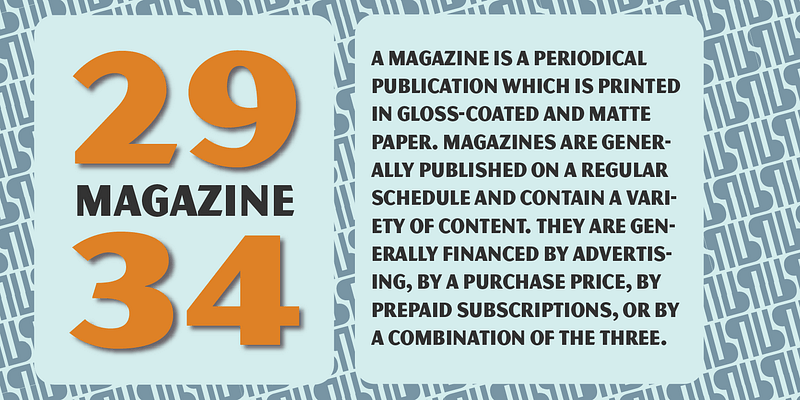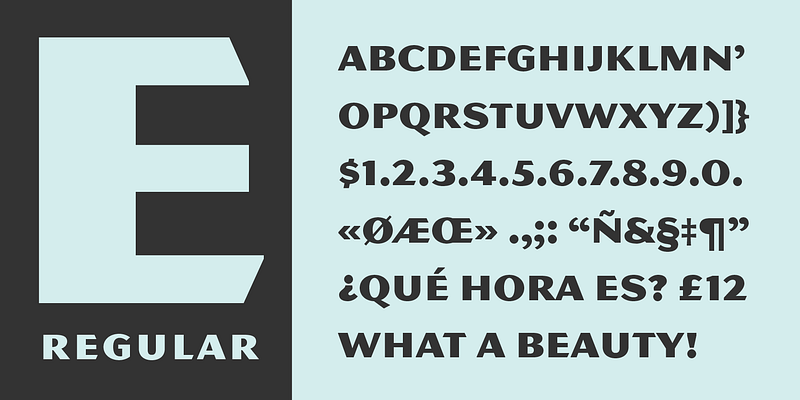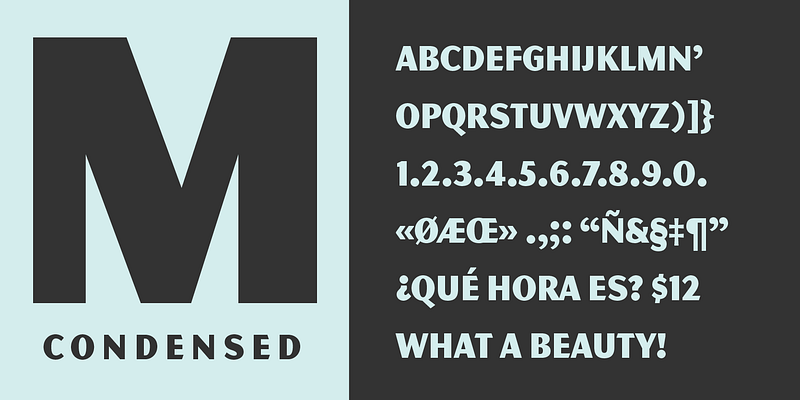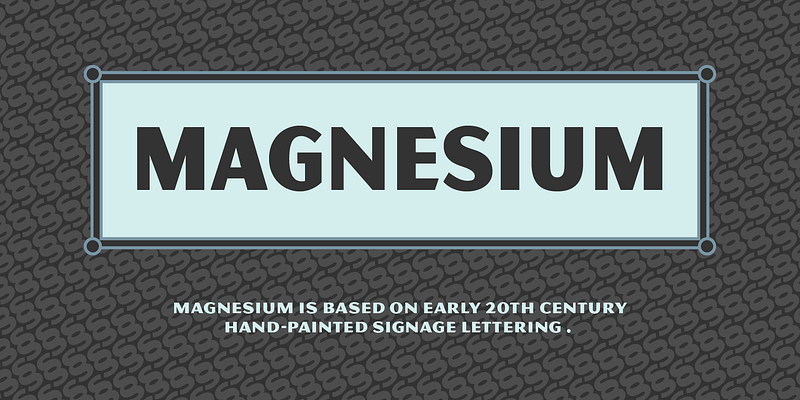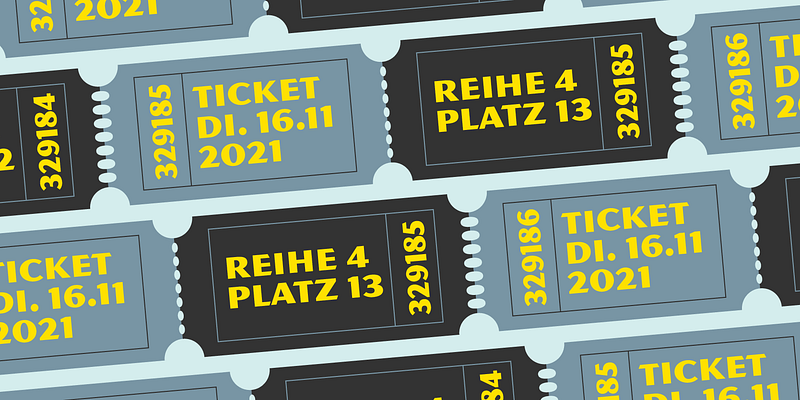
Die MVB Magnesium von Mark van Bronkhorst basiert auf seinen Eindrücken eines Schriftstils, den man häufig auf handgemalten Schildern des frühen 20. Jahrhunderts sieht. Mit ihren dick-dünnen Strichen und abgewinkelten Enden ist die MVB Magnesium eine wärmere, weniger verbreitete Alternative, wenn man eine serifenlose Schrift in Großbuchstaben verwenden möchte. Sie ist in zwei Breiten erhältlich.